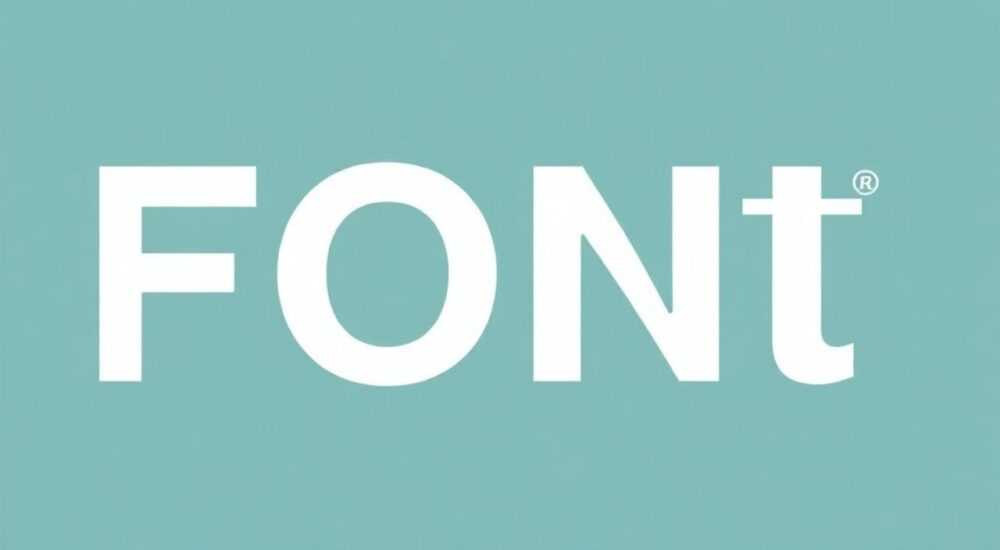
Как скопировать шрифт с картинки в фотошопе
Когда вы работаете с визуальным контентом, часто возникает необходимость скопировать шрифт с изображения для использования в собственных проектах. Эта задача может показаться сложной, особенно если вы новичок в Photoshop, но на самом деле существует несколько эффективных методов, позволяющих достичь желаемого результата. Интересно, что современные технологии значительно упростили этот процесс, делая его доступным даже для начинающих дизайнеров. В этой статье мы подробно разберем все способы копирования шрифтов, включая пошаговые инструкции и профессиональные советы.
Основные методы определения шрифта с картинки
Существует три основных подхода к решению задачи копирования шрифта с изображения в Photoshop. Первый метод предполагает использование специальных сервисов распознавания шрифтов, второй — непосредственную работу с исходным файлом через графический редактор, а третий — комбинацию автоматических и ручных техник. Каждый из этих подходов имеет свои преимущества и особенности применения.
• Сервисное распознавание через онлайн-платформы
• Ручной анализ через Photoshop
• Комбинированный подход с использованием различных инструментов
Примечательно, что выбор метода зависит от конкретной ситуации: качества исходного изображения, наличия дисторсии или других искажений, а также требуемой точности копирования.
Использование онлайн-сервисов для распознавания шрифтов
Современные технологии предлагают множество специализированных сервисов для автоматического распознавания шрифтов. Среди наиболее популярных можно выделить WhatTheFont, FontSquirrel Matcherator и Google Fonts Matcher. Эти платформы используют сложные алгоритмы машинного обучения для анализа загруженных изображений.
Важно отметить, что точность распознавания напрямую зависит от качества исходного изображения. Для достижения максимальной эффективности рекомендуется использовать изображения с высоким разрешением и минимальными искажениями.
Пошаговая инструкция работы с Photoshop
Для тех, кто предпочитает работать непосредственно в Photoshop, существует несколько эффективных техник копирования шрифтов. Рассмотрим подробный алгоритм действий:
• Шаг 1: Откройте изображение в Photoshop и увеличьте масштаб до 200-300%
• Шаг 2: Используйте инструмент «Прямоугольная область» для выделения текстового элемента
• Шаг 3: Примените фильтр «Найти края» (Filter > Stylize > Find Edges)
• Шаг 4: Отрегулируйте яркость и контрастность для четкого выделения символов
• Шаг 5: Создайте новый текстовый слой поверх оригинала
• Шаг 6: Поэкспериментируйте с различными шрифтами из библиотеки Photoshop
Помните, что ключ к успеху лежит в внимательном сравнении деталей оригинального текста с тестовыми образцами. Начинайте с базовых характеристик: толщины линий, засечек и пропорций букв.
Анализ характерных особенностей шрифта
Для точного подбора шрифта необходимо учитывать множество факторов. Вот основные параметры, на которые стоит обратить внимание:
• Наличие и форма засечек
• Пропорции букв (ширина/высота)
• Толщина основных и вспомогательных штрихов
• Форма округлых элементов
• Расстояние между символами
• Особенности начертания отдельных букв
Профессионалы часто создают таблицу сравнения различных шрифтов, фиксируя их ключевые характеристики. Этот подход позволяет систематизировать информацию и ускорить процесс подбора.
Автоматизация процесса с помощью плагинов
Photoshop предлагает широкие возможности для автоматизации работы со шрифтами через специальные плагины. Наиболее популярными являются FontHero и TypeKit Integration. Эти расширения значительно упрощают процесс поиска и сравнения шрифтов прямо в рабочей среде.
Важно отметить, что использование плагинов не только экономит время, но и повышает точность подбора благодаря продвинутым алгоритмам анализа.
Экспертное мнение: советы от профессионала
Александр Петров, ведущий дизайнер студии VisualCraft с 15-летним опытом работы в сфере графического дизайна, делится своими наблюдениями: «Многие начинающие дизайнеры совершают одну и ту же ошибку — пытаются найти абсолютно идентичный шрифт. В реальности гораздо важнее подобрать гармоничную замену, которая сохранит общее настроение композиции.»
В своей практике Александр часто сталкивается с ситуациями, когда точное совпадение невозможно. «В таких случаях я рекомендую сосредоточиться на ключевых характеристиках шрифта: его ‘характере’ и эмоциональной составляющей. Например, если оригинал — это строгий геометрический шрифт, то лучше выбрать похожий по духу вариант, чем пытаться точно воспроизвести каждую деталь.»